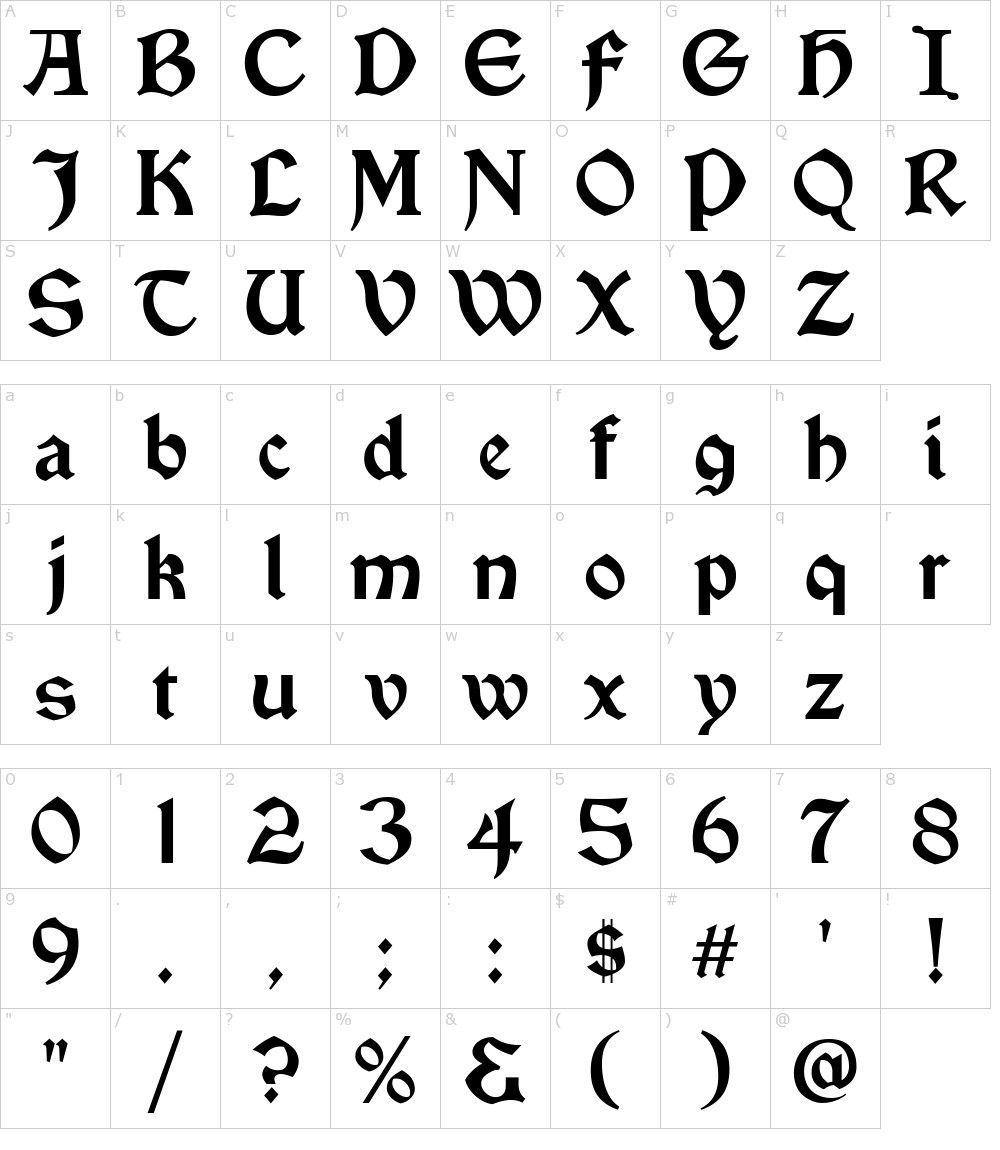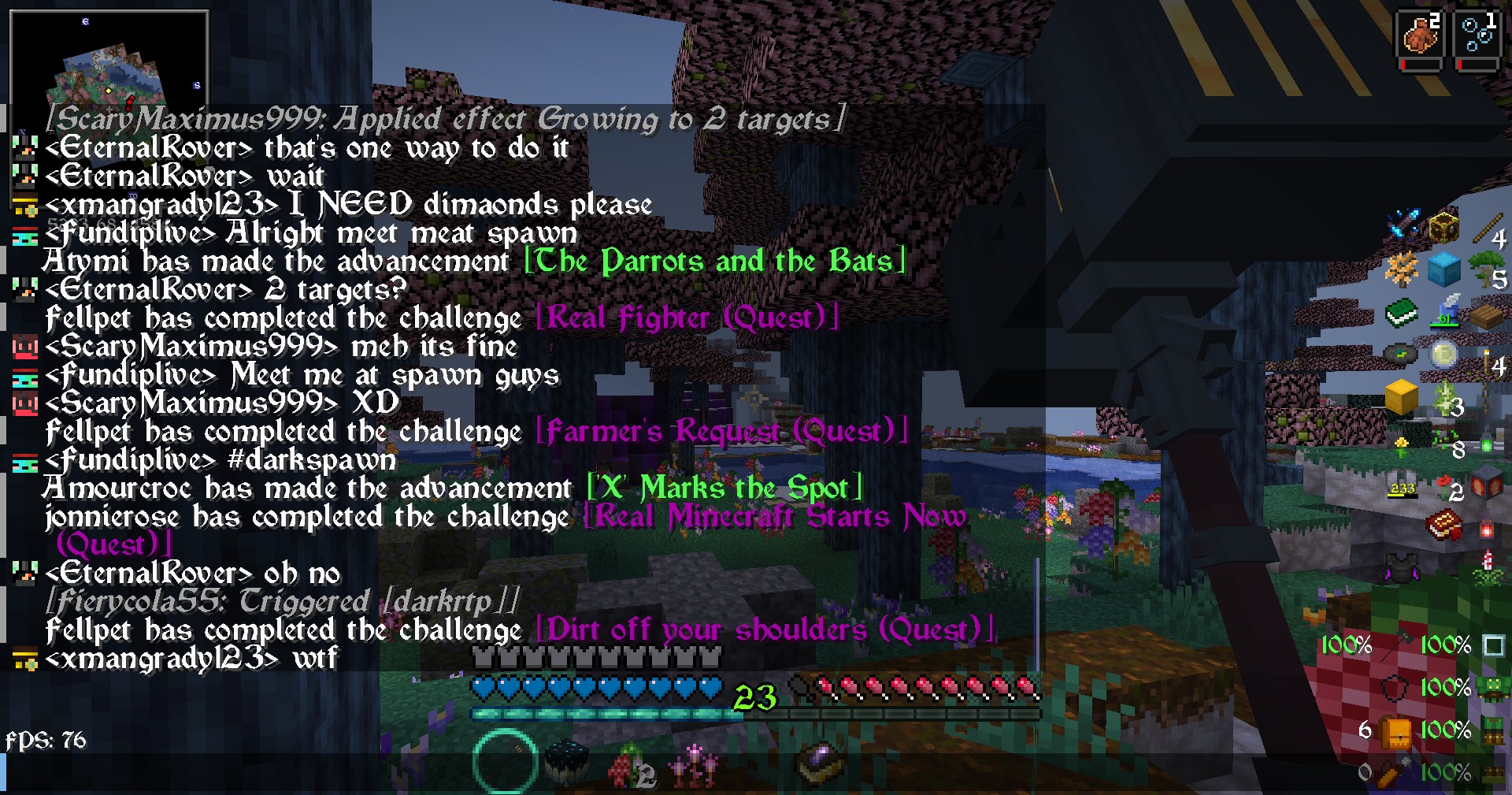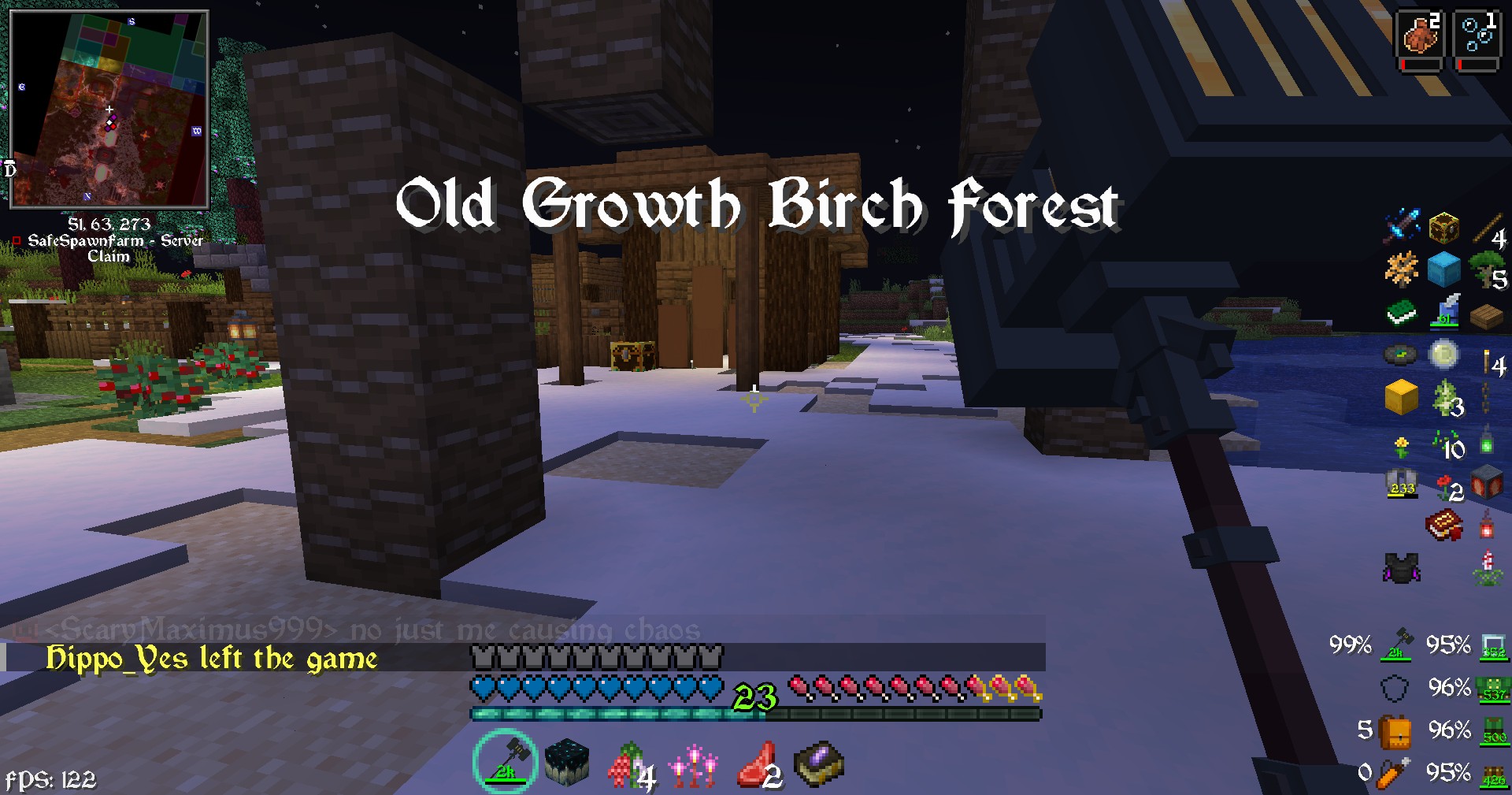
Средневековый шрифт добавит уникальную атмосферу в игре.
Погрузитесь в атмосферу средневековья с уникальным шрифтом Gothic Medieval RPG Font для Minecraft. Этот мод открывает новые горизонты вашего игрового опыта, добавляя стильный и читаемый шрифт, который идеально вписывается в темную фэнтезийную атмосферу. Созданный для мода DarkRPG, данный шрифт теперь доступен каждому любителю Minecraft, стремящемуся к максимальной аутентичности.
Шрифт Gothic Medieval RPG Font не только добавляет эстетическое разнообразие, но и помогает создать уникальную атмосферу в вашей игре. Благодаря своему дизайну, он идеально подходит для ролеальных серверов и одиночных приключений, где важно сохранить дух средневекового фэнтезийного мира.